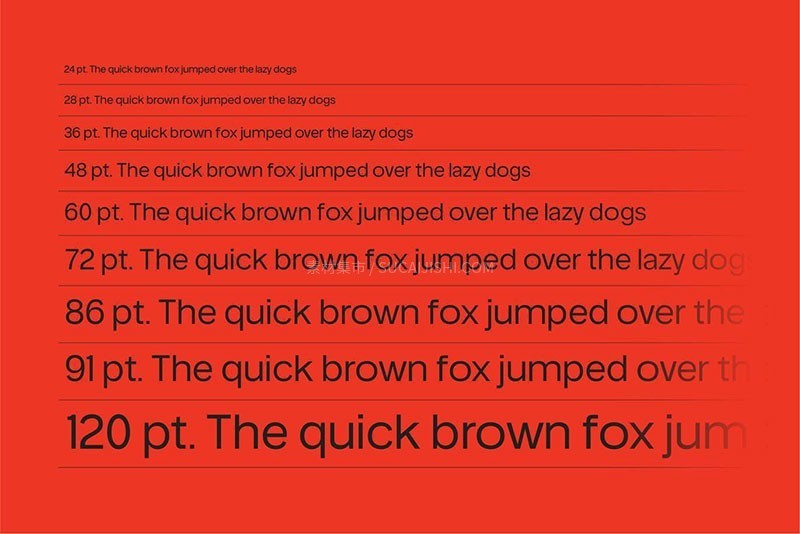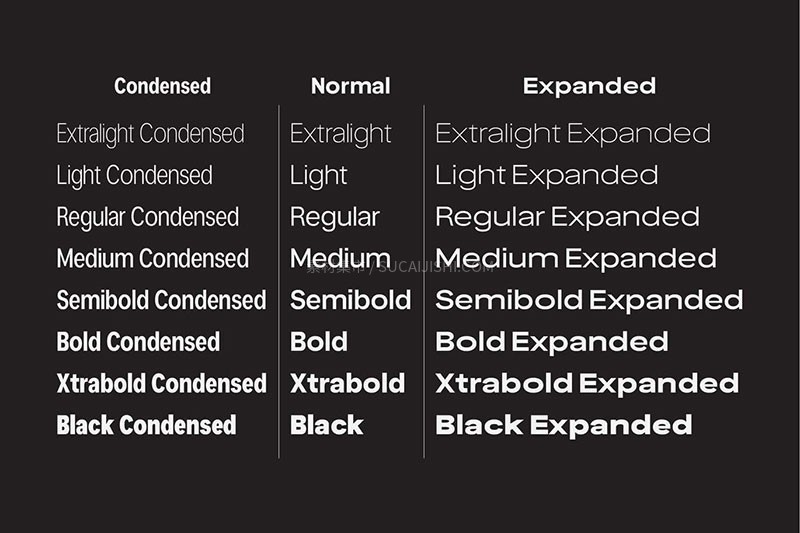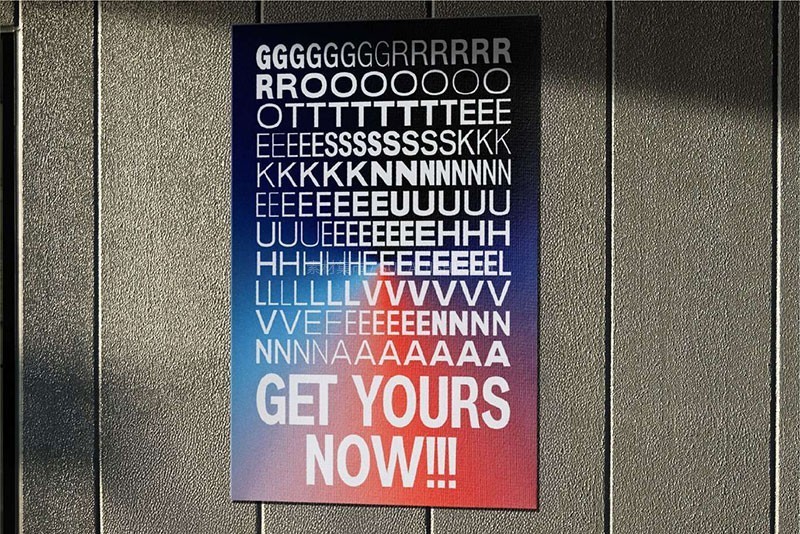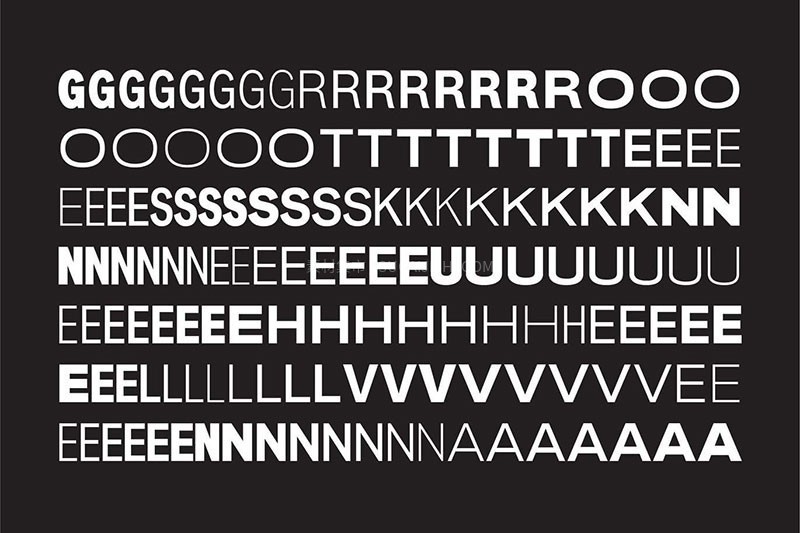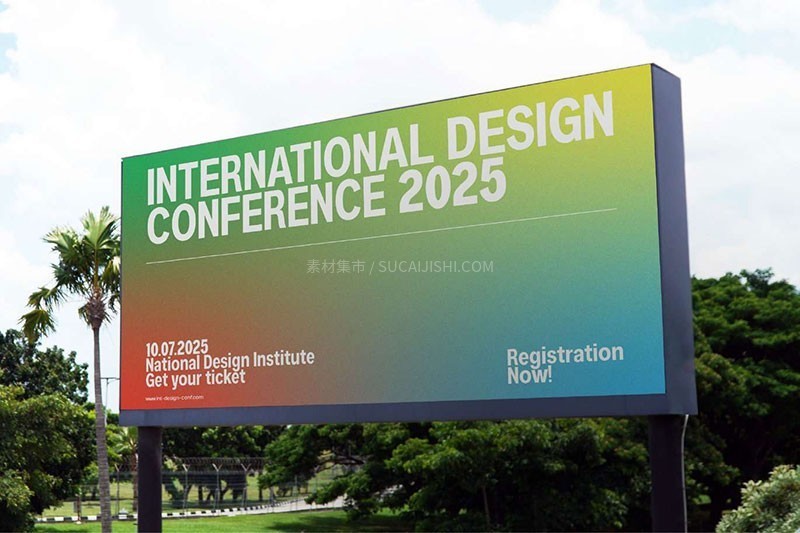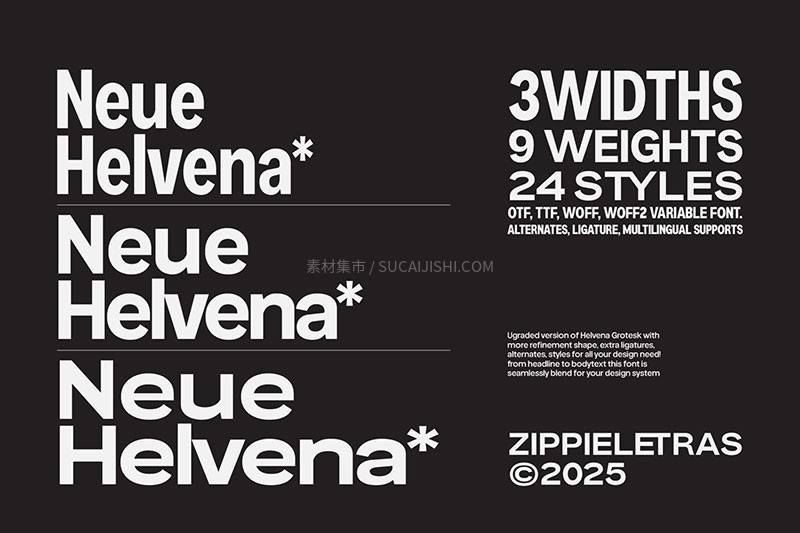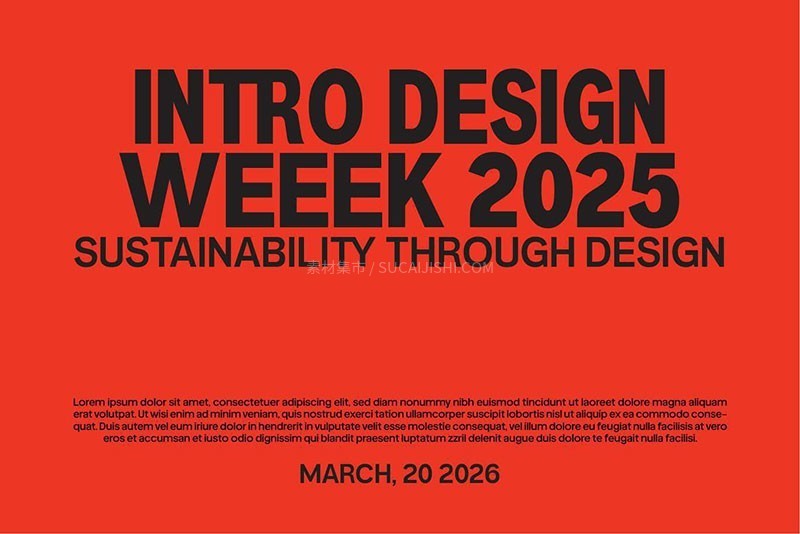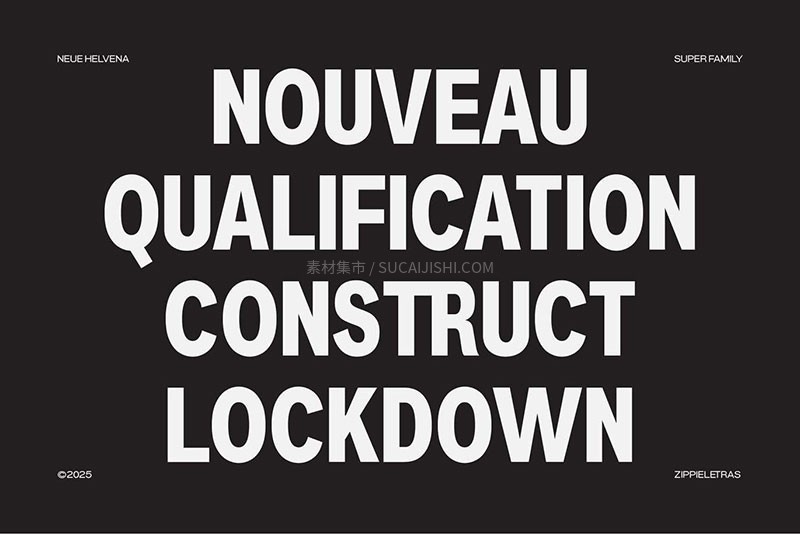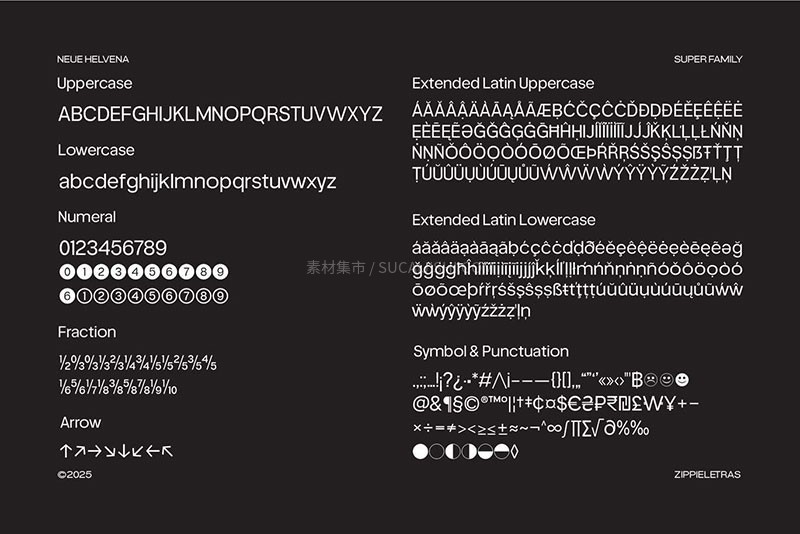
Neue Helvetica 经典重制无衬线字体
Neue Helvetica 在保留 Helvetica 原有经典风格的基础上,进行了一系列美学和技术上的改进,使其更适应数字化时代的需求,提供 24 种风格(从特细到特黑,从窄体到宽体),适用场景: 品牌形象和标志设计、企业及编辑用途(杂志、年度报告)、数字标题和网页设计(UX/UI)、广告与海报设计、响应式排版。